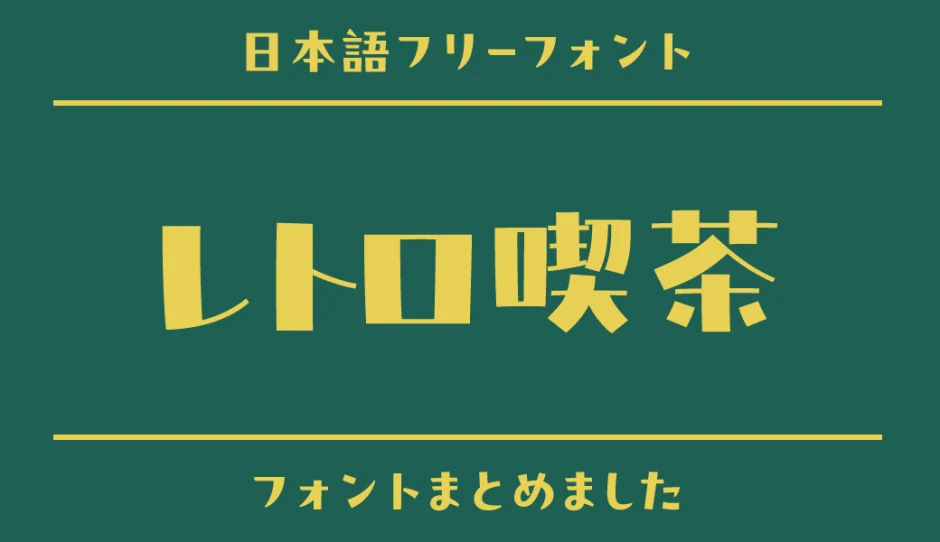
本記事では、「レトロ喫茶」の世界観にぴったりな日本語フリーフォントを紹介します。珈琲の香りが似合う落ち着いたメニューから、プリンやクリームソーダの楽しげなPOPまで、文字の選び方でお店の雰囲気が変わります。
レトロ喫茶らしさを作るポイントは、懐かしさの方向を決めること。静かな純喫茶には活字の風合いを、洋館風の喫茶室には装飾のある書体を、明るいデザート紹介には丸文字やポップなカタカナを合わせると、伝えたい印象がまとまります。今回は店名やメニュー、ショップカードなどに使いやすい10書体を選びました。
カタカナ専用のフォントや漢字が一部のみのフォントも含みます。商品名を目立たせる書体と、価格や説明を読みやすく見せる書体を分けると、雰囲気と使いやすさを両立できます。
「レトロ喫茶」におすすめの日本語フリーフォント
Oradano明朝
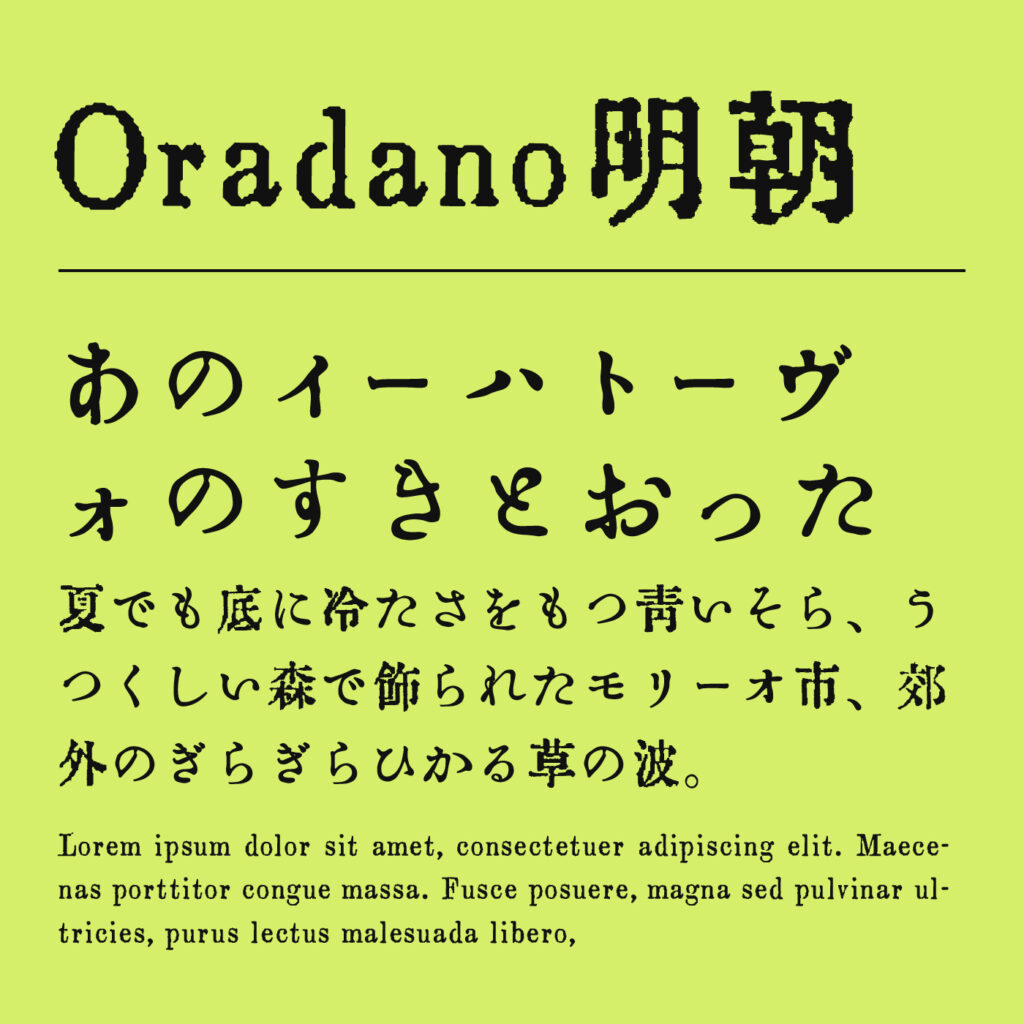
活版印刷を思わせる字の表情が、長く親しまれてきた喫茶店の空気に合います。
落ち着いた純喫茶を表現するなら、まず候補にしたい明朝体です。珈琲の銘柄や店の紹介文に使うと、古い本の一節のような趣が生まれます。墨色の文字とシンプルな罫線だけでも雰囲気を作りやすく、装飾を増やしたくない紙面にもおすすめです。細かな質感を見せる見出しと、価格などの読みやすい情報を分けると、実用的なメニューにまとまります。
なぎの
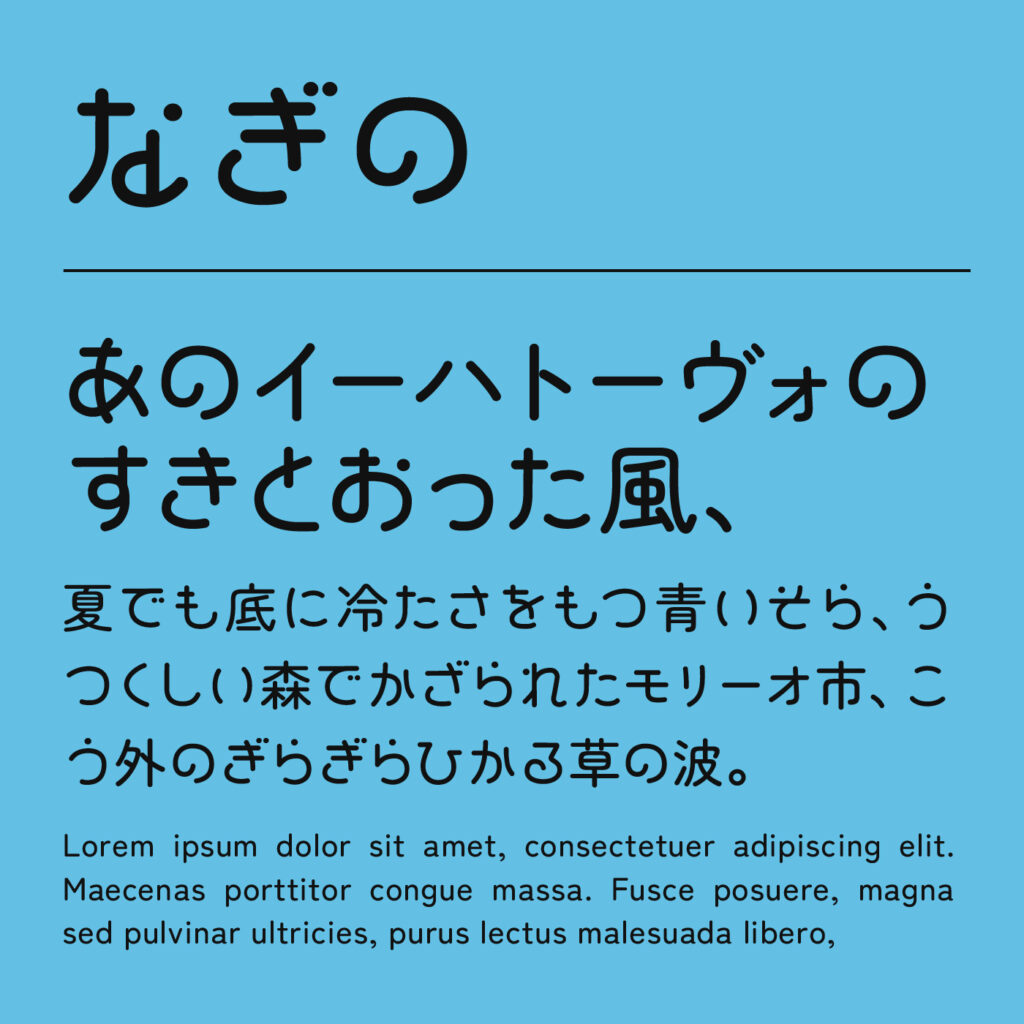
丸くふくらんだひらがなが、懐かしく親しみやすい印象を作ります。
かたい活字の雰囲気より、手描きの看板のような温かさを出したいときに向いています。ひらがなを使った店名や、季節の甘味の見出しに合わせると、独自の字形がほどよいアクセントになります。カタカナや漢字などはZEN丸ゴシックとの組み合わせなので、すべての文字が同じ装飾を持つわけではありません。使う店名を実際に組んで選ぶのがおすすめです。
になロマン
装飾のある字形で、クラシックな喫茶室らしい華やかさを加えられます。
洋館の照明やステンドグラスを思わせる空間に、少しロマンチックな文字を合わせたいときの候補です。かなで書いたメニュー名や短いタイトルに使うと、文字そのものが飾りになります。本文まで同じ書体で埋めず、材料の説明や価格にはシンプルな書体を合わせると、華やかさが引き立ちます。漢字を含む店名には、別書体との組み合わせが必要です。
ナイショ文字
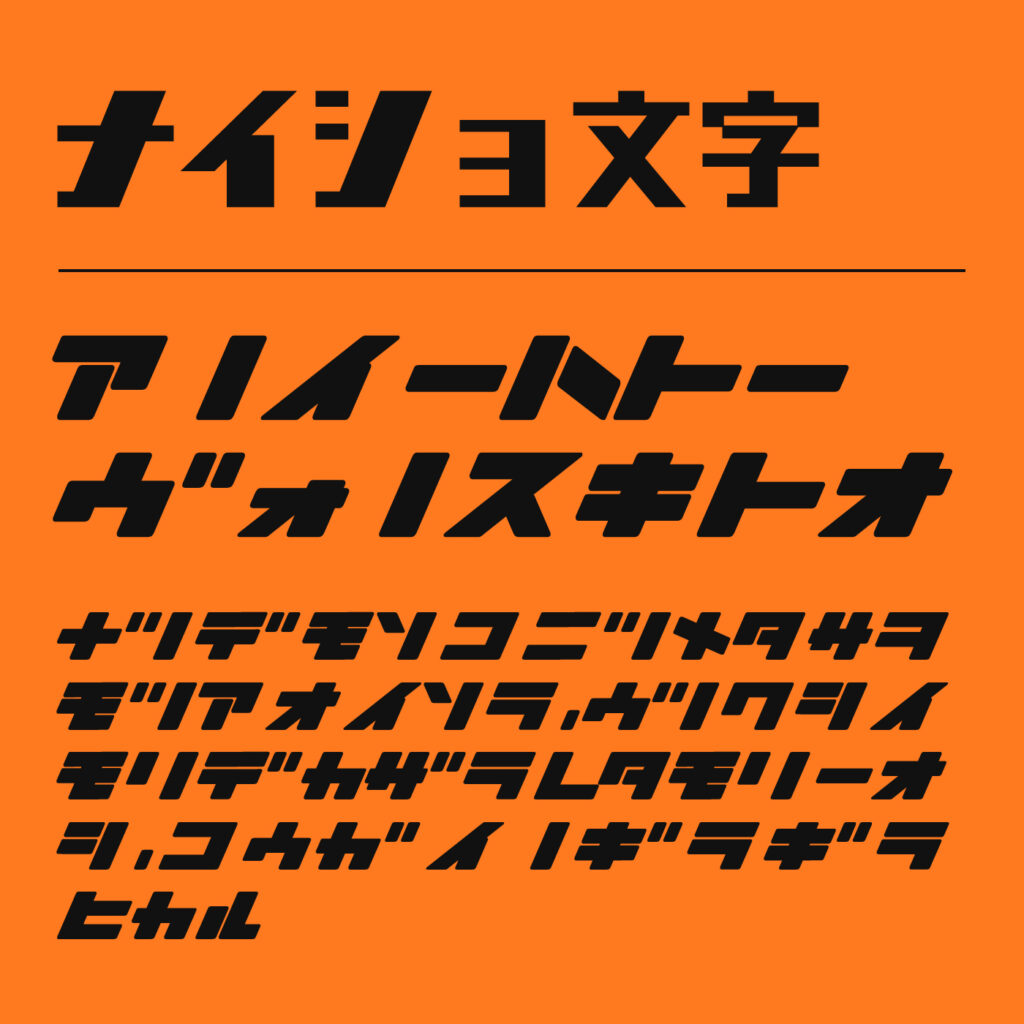
縦線と横線の太さの差が、昭和の看板を連想させる書体です。
カタカナの商品名を、ひと目で記憶に残る見出しにしたいときに向いています。「ナポリタン」などを大きく配置すると、食堂や喫茶店の看板のような存在感が出ます。短い言葉を主役にし、背景や飾りを控えめにまとめると独特の形を楽しめます。漢字は一部のみの収録なので、店名やメニュー全体をこの書体だけでそろえる前に確認しましょう。
ミスターグレイ
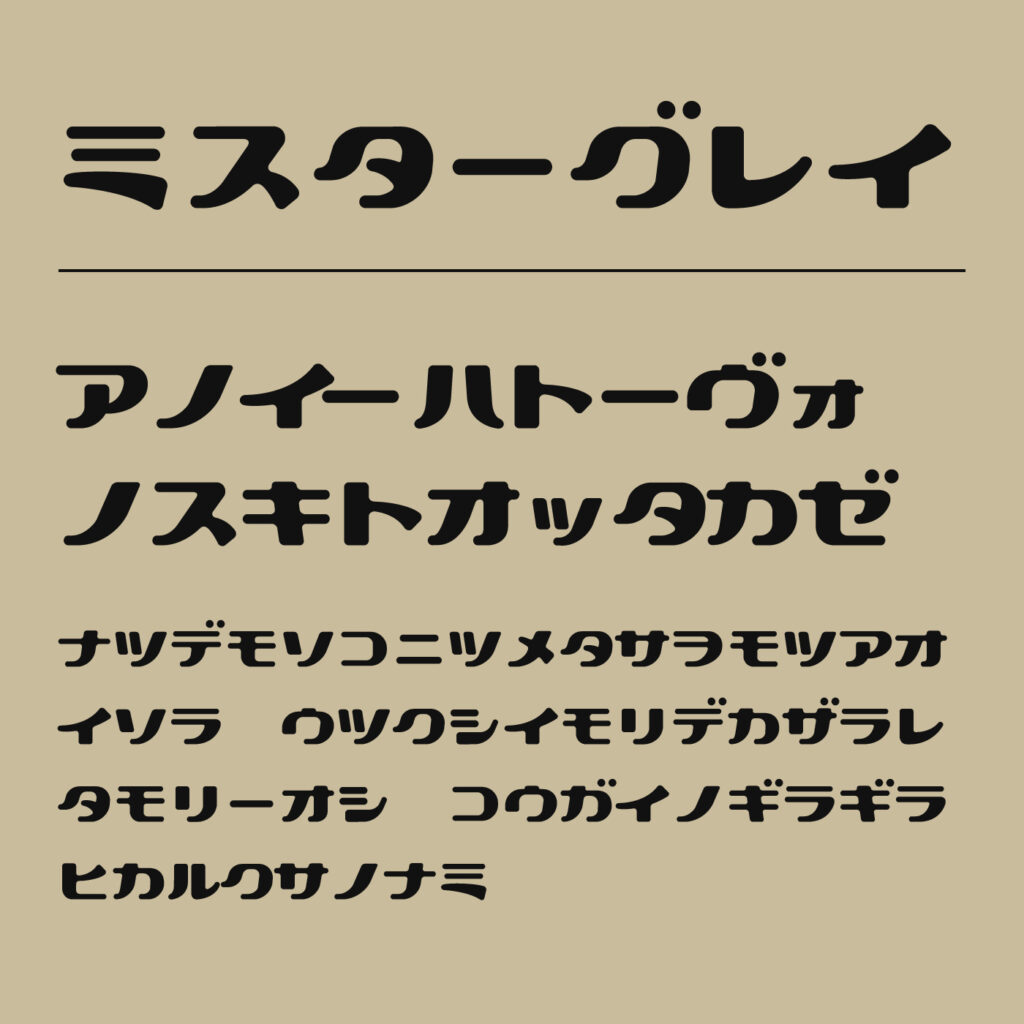
懐かしさの中にポップな楽しさがある、カタカナ専用フォントです。
はちまるポップ(Hachi Maru Pop)
丸文字の懐かしさで、かわいらしい喫茶店の雰囲気を演出できます。
80年代風の丸文字を取り入れたいときに使いやすい書体です。フルーツパフェやクリームソーダの紹介など、色鮮やかな写真と合わせると親しみやすく仕上がります。漢字も使えるため、商品名から短い説明まで印象をそろえやすいのも魅力です。細い線が背景に埋もれないように、写真に直接重ねる場合は文字の周囲に余白を確保しましょう。
SY気もミン
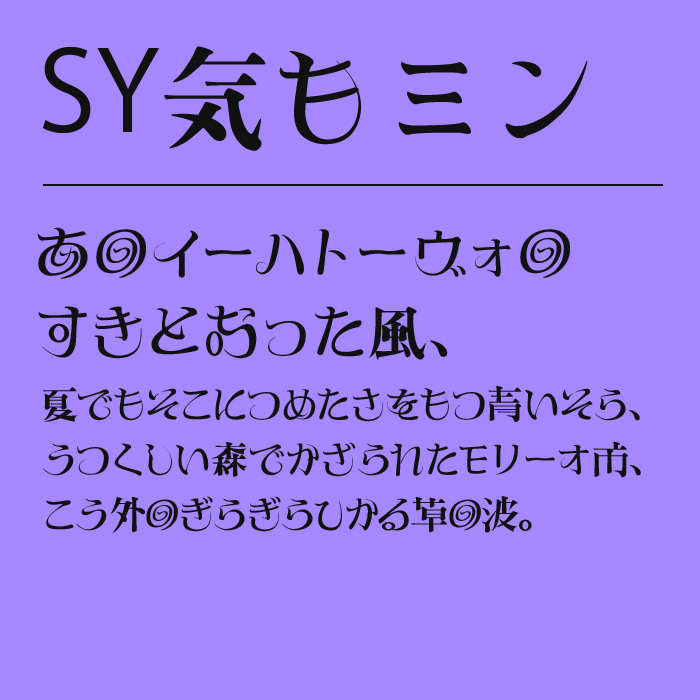
明朝体にカールのような飾りが入り、上品さと遊び心を添えられます。
古い洋菓子店を思わせる華やかさを、文字で表現したいときに向いています。焼き菓子の名前や紅茶メニューの見出しに使うと、端正な骨格と装飾の組み合わせが活きます。飾り罫を多く足すより、余白の中に少し大きく置いて字形を見せる使い方がおすすめです。落ち着いた純喫茶に、甘く優雅な要素を少し加えたいときにも候補になります。
ぽっぷまる
サインペンで書いたような丸い文字で、気取らない喫茶店らしさが出せます。
昔から通っているお店の手書きメニューを思わせる、温かい表情が魅力です。モーニングや本日のケーキの案内など、毎日の情報をやさしく見せる用途に向いています。丸い字形とほどよい太さを活かして、短い文章をゆったり配置すると読みやすくなります。大人っぽい活字系の店名と組み合わせれば、懐かしさに親しみやすさを足せます。
ひょうきんな!?ポップ体
昭和のテレビ番組を思わせる手描き文字で、楽しいレトロ感を作れます。
静かな喫茶室のロゴより、期間限定メニューや催しのお知らせを目立たせたい場面に向いています。太さや形に表情があるので、短い見出しでも楽しげな印象になります。鮮やかな商品写真に合わせたり、丸い吹き出しに収めたりすると、昭和レトロのポップな側面を表現できます。情報を詰め込みすぎず、一番伝えたい言葉を主役にして使うのがおすすめです。
タイムマシンわ号
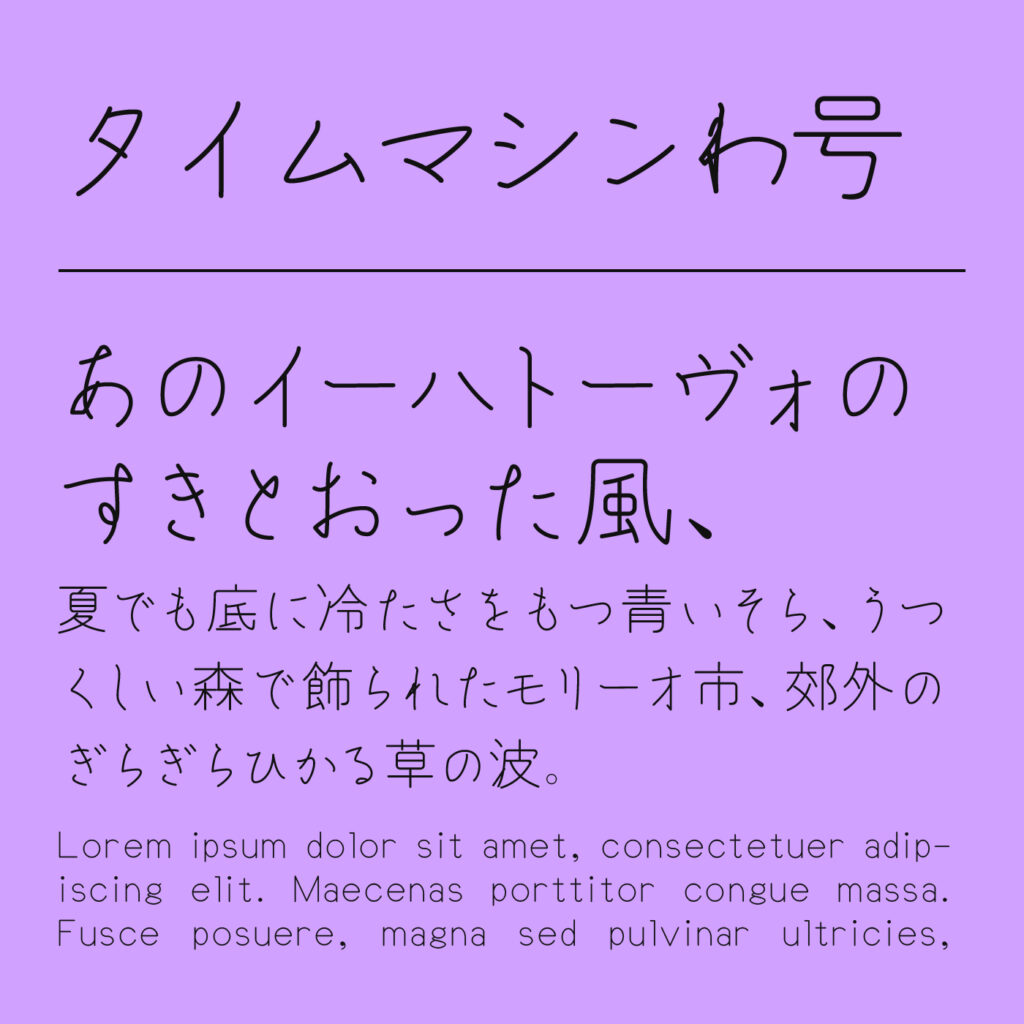
古風なかなと独特な漢字の組み合わせが、懐かしさに新鮮さを加えます。
昭和の喫茶店をそのまま再現するより、今の感覚でレトロを楽しむデザインに向いています。珈琲豆の商品名や、架空の喫茶店を題材にした制作物に使うと、ひと癖ある文字が印象に残ります。かなと漢字で表情が変わるため、実際に使う言葉で全体のリズムを見ると選びやすくなります。短い見出しを中心に使い、説明は素直な書体で添えるとまとまります。